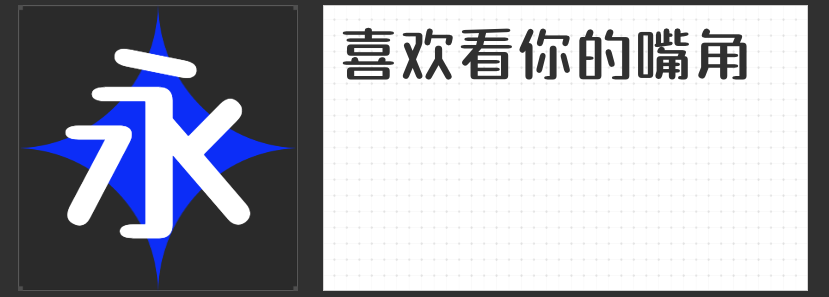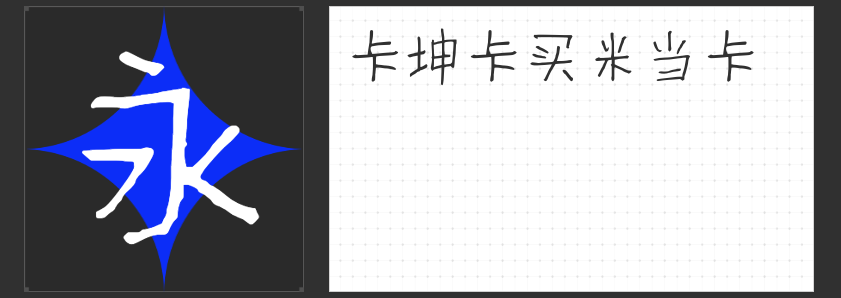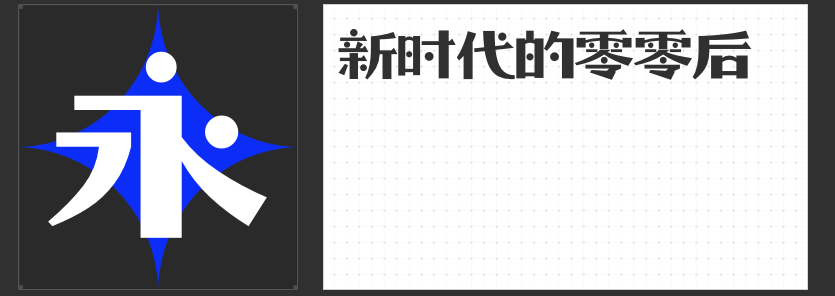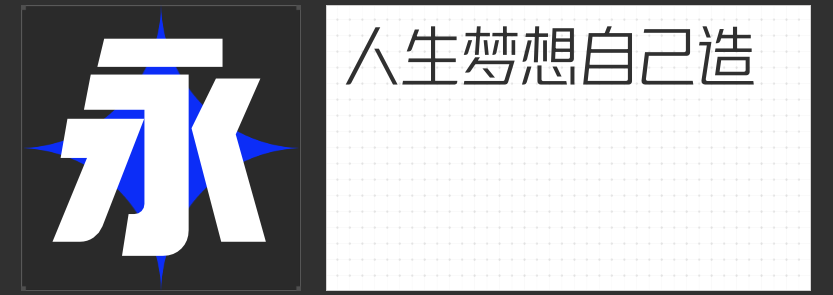
励字造梦,共绘未来 —— 阿里妈妈合作精选字体推荐
在数字创意的浩瀚星空中,字体不仅是信息的载体,更是情感的桥梁与个性的彰显。励字造梦根据阿里妈妈的选择,精心推荐四款创意字体,旨在为您的品牌故事增添无限魅力与可能。
1.励字笑语声声简
这款字体以其圆润流畅的线条,仿佛能听见字里行间的欢声笑语。它适用于轻松愉悦的场景,如节日促销、社交媒体互动,让每一条信息都洋溢着温暖与活力,瞬间拉近与受众的距离。
2.励字造梦简 可变字体
创新不止,梦想不息。作为可变字体的佼佼者,“励字造梦简 可变字体”能够根据设计需求自由调整粗细、宽窄,甚至倾斜度,为设计师提供前所未有的创作自由度。无论是现代简约还是复古风情,一键切换,轻松驾驭各种风格,让创意无限延伸。
3.字恋狂零零后简繁
专为年轻一代打造的字体,“字恋狂零零后”融合了简体的简洁与繁体的韵味,既保留了传统文化的精髓,又不失时尚前卫的气息。它适用于青春、潮流的品牌形象塑造,让文字成为连接过去与未来的桥梁,触动年轻消费者的心弦。
4.MyFont萨瓦迪卡简 细体
一抹异域风情,一抹细腻雅致。“MyFont萨瓦迪卡简 细体”以其独特的泰式韵味和细腻的笔触,为设计作品增添一抹清新脱俗的异国色彩。无论是旅游宣传、文化展览还是时尚设计,它都能完美融入,让人仿佛置身于温暖的东南亚阳光下,感受那份悠闲与自在。
四款字体,四种风情,励字造梦与阿里妈妈的合作,不仅是对字体艺术的致敬,更是对未来创意趋势的深刻洞察。选择一款,让您的品牌故事在字里行间绽放光彩,共创美好未来。